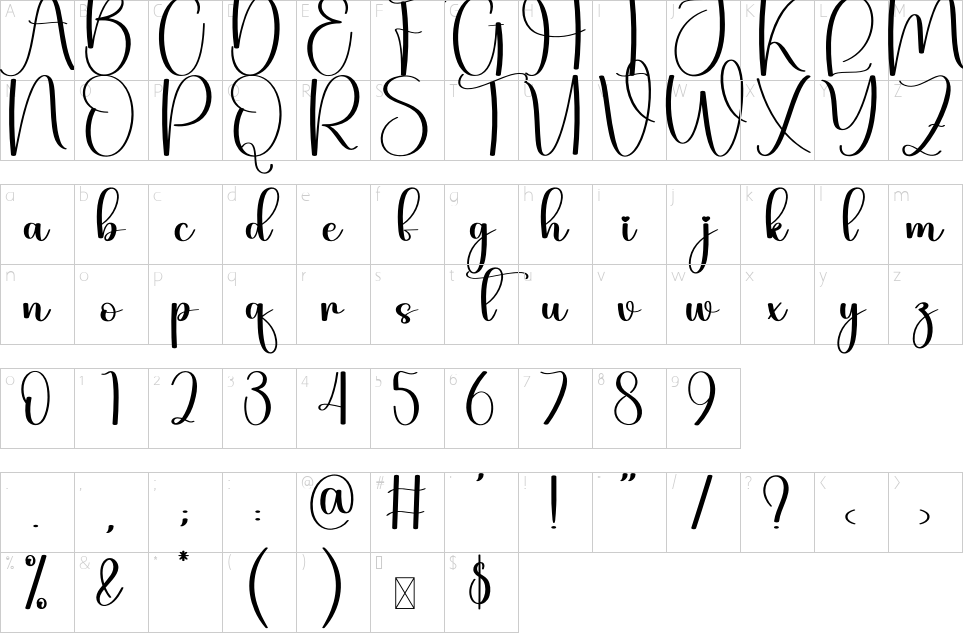
Descubra a delicadeza do ‘Diary Love Font’, uma elegante fonte feita por scratchones especialmente para registradores de vida diárias. Inspirada no registro das pequenas observações e sentimentos, esta font oferece um toque personalizado que adiciona sabor aos seus textos diários. Com uma aparência suave e sem ser muito detalhada, permite que você personalize seu trabalho com facilidade e estilo. Seja para gravações de diário pessoal ou para um blog delicado, ‘Diary Love’ é a escolha perfeita. Esta font foi baixada 361 vezes, o que demonstra sua popularidade entre os criadores de conteúdo online. Descubra por si mesmo as qualidades únicas desta fonte e transforme seus registros em um verdadeiro capricho visual.